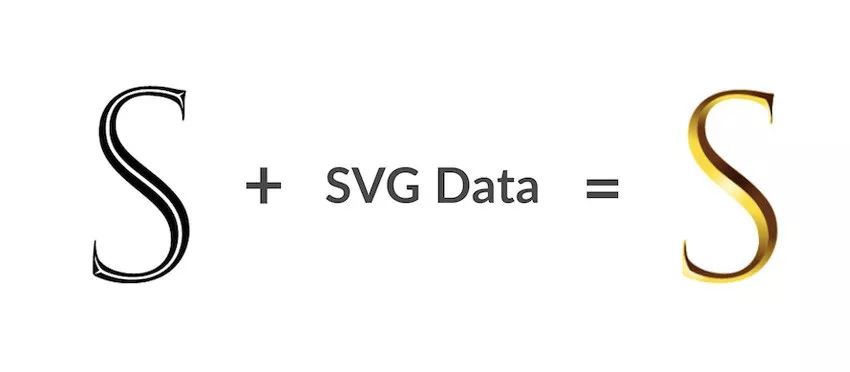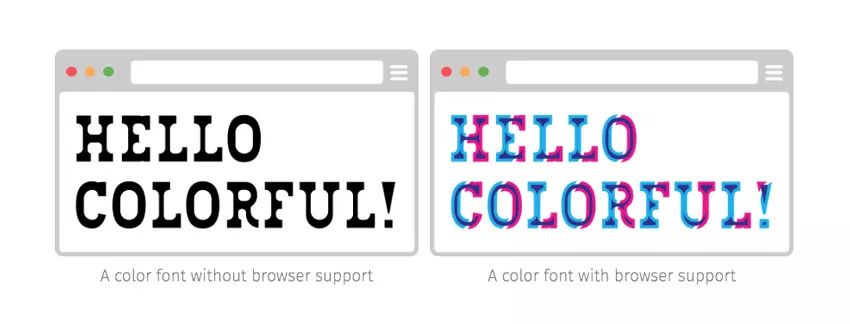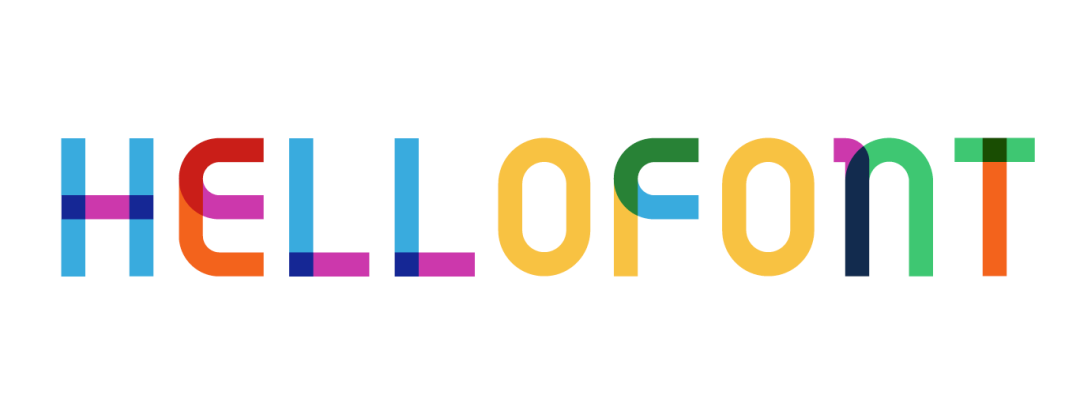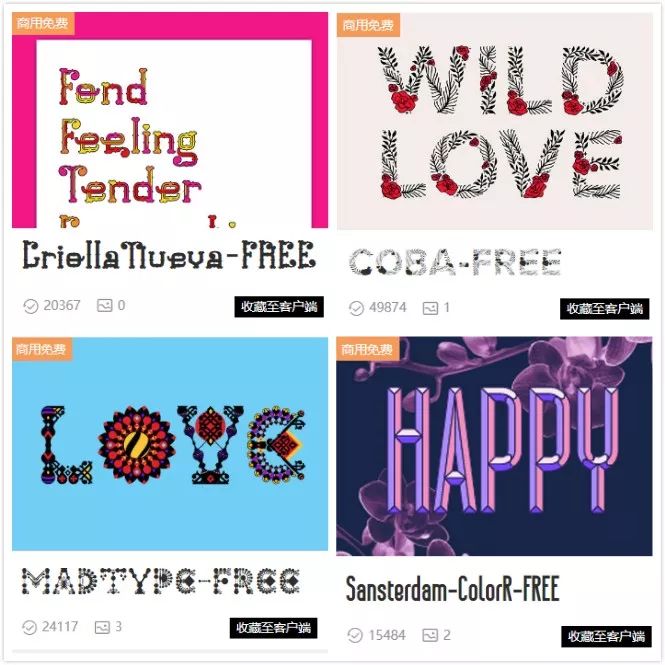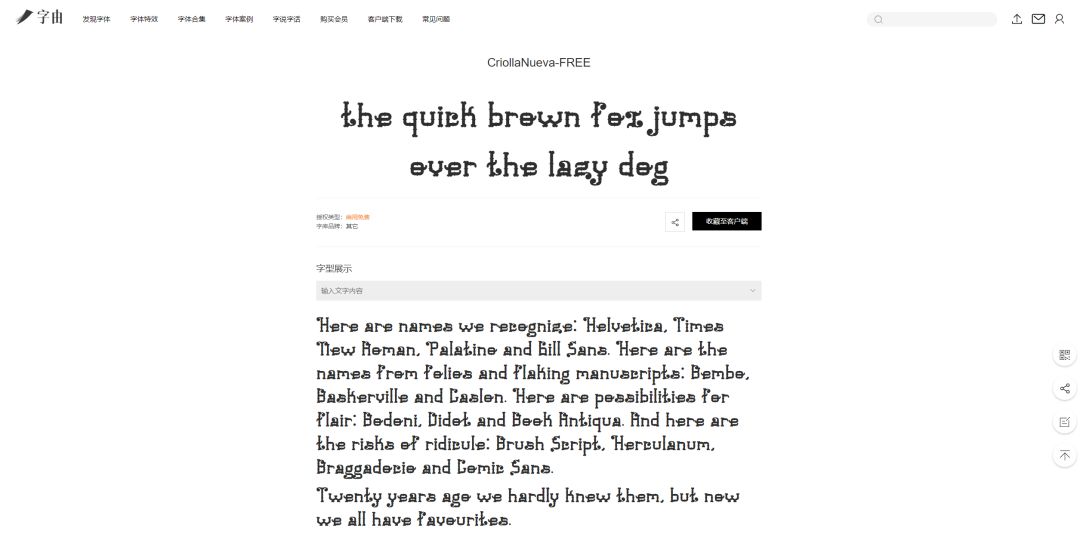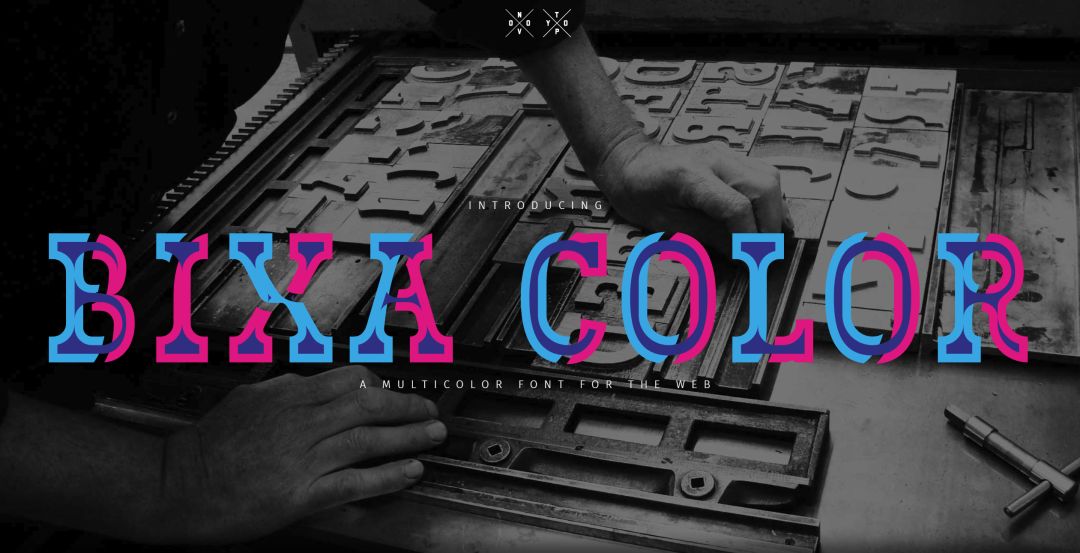
彩色字体分享,今天灵魂不在线?快用彩色字体激一下~
就像你可能没想过,字体有一天也会变得五彩缤纷~
这不是一个新话题,但未来一定会成为某种趋势。简单来说,彩色字体就是将特效融合到了字体文件中,形成了矢量的OpenType-SVG。
听起来跟我们会员的字体特效有点像,但又不完全一样,它是西文,也不能变换字体~
样式更是固定的,而字由的特效,可以拖到AI中变颜色~
可这依然不影响彩色字体的C位,谁叫人家长得好看!字由也上了几款,还是商用免费。
目前大多数浏览器、字体预览还不支持,所以你只能看到原始版。
但只要放进阿杜比爸爸,还是完全没问题的,看我72变!
我期待着彩色字体越来越多的那一天~